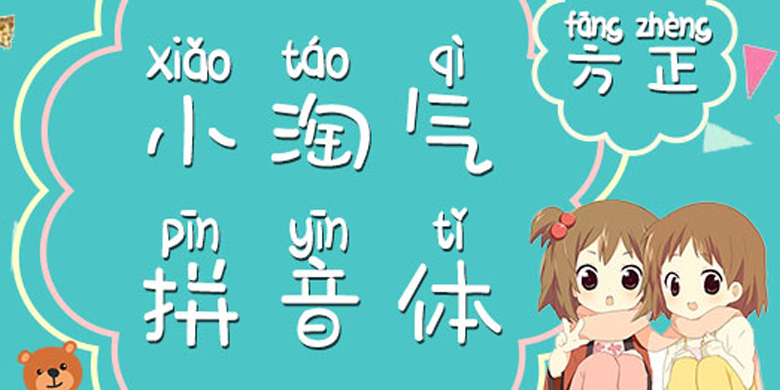
方正手迹-小淘气拼音体
字体品牌: 方正手迹 设计师:高宇 字体分类:创意书写 字体属性:精品字 字符集:大陆简体(GB2312-80) 发布时间: 2020
简洁的笔画,轻松大方的字形,统一的字面大小,圆润的转角,温婉迷人,少女气息满满。适用于少年儿童类的书刊、品牌广告和产品包装设计,以及社交网络的个性化用字。